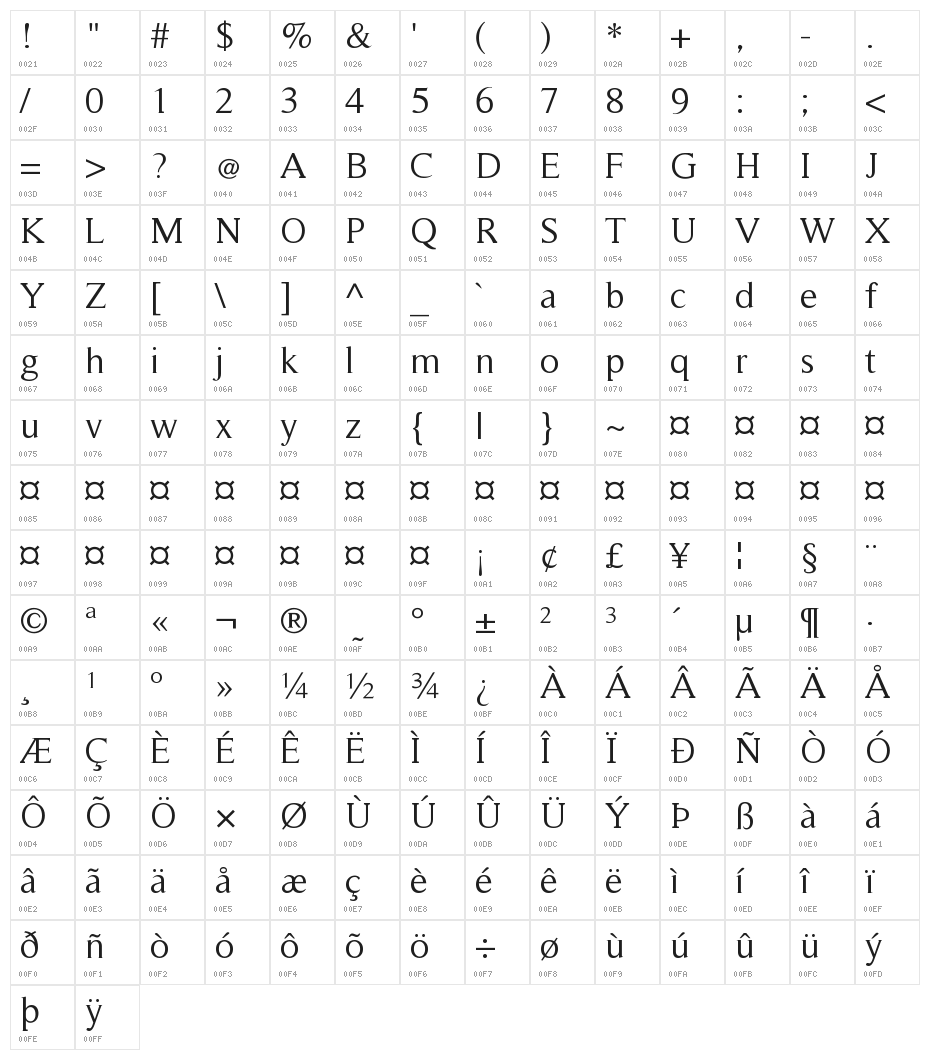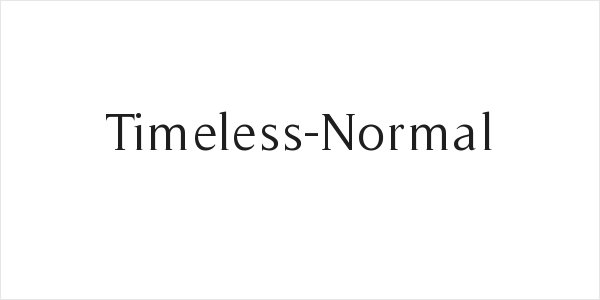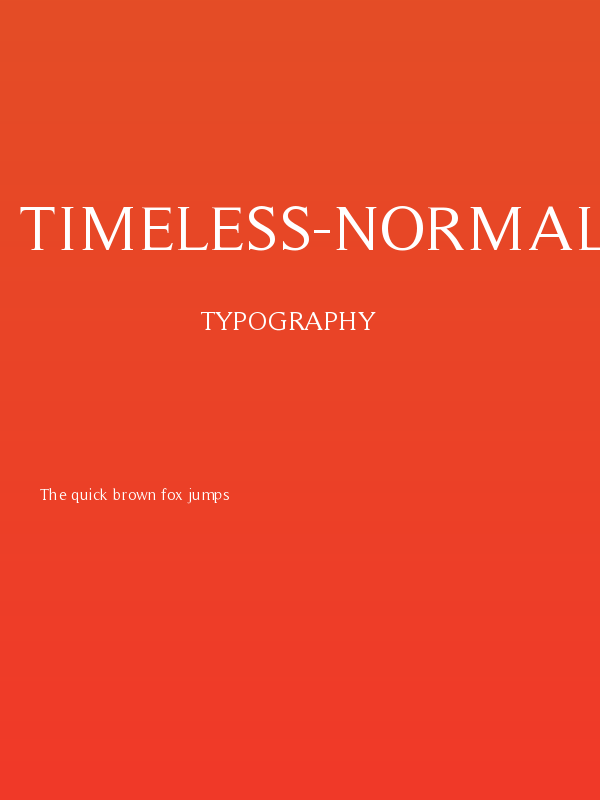
Timeless-Normal Font
✎ Serif
| Kategorien | Serif |
| Gesamtstil | Classic |
| Anwendungsfall | Headlines, Body text, Logos |
| Vorgeschlagene Projekte | Ideal for editorial design, book covers, formal invitations, and branding projects that require a touch of sophistication. |